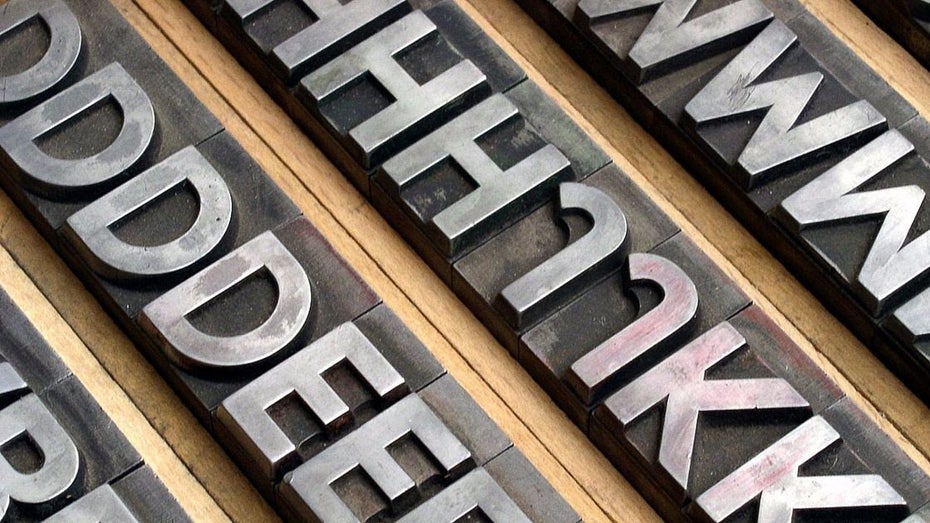
Das Geheimnis guter Typographie: Einfache Tipps für mehr Lesekomfort
Typographie: Schon mit geringstem Aufwand lassen sich Texte deutlich besser lesbar gestalten. (Foto: Pixabay)
Natürlich ist Typographie seit jeher eines der wichtigsten Elemente im klassischen Design. Studierst du Grafikdesign oder verwandte Fächer, so gehört Typographie direkt im ersten Semester zu deinem täglich Brot. Wir wollen hier aber nicht auf akademischen Niveau theoretische Abhandlungen verfassen.
Vielmehr geht es darum, auch dem Nichtdesigner den Wert der Umsetzung typographischer Grundlagen zu vermitteln. Mit den folgenden Tipps gestaltest du deine Texte wesentlich lesbarer und sorgst noch dazu für eine bessere Auffindbarkeit im bereits randvollen Weltennetz.
Beginnen wir mit den Tipps für komfortableres Lesen, die Designer Luke Jones vor wenigen Tagen im InVision-Blog zum Besten gab. Es handelt sich um drei kleine Änderungen, die sich ohne großen Aufwand an jedem Text vollziehen lassen. Nach dem zweiten oder dritten Mal werdet ihr diese Tipps so selbstverständlich anwenden, als hättet ihr es noch nie anders gemacht.
Wenn ihr mehr oder weniger regelmäßig ins Netz schreibt, dann ist euch schon bekannt, dass die Einhaltung der korrekten Hierarchie eines Textes ein wichtiger Faktor für die Auffindbarkeit eurer Inhalte in Suchmaschinen ist. Wahrscheinlich achtet ihr schon aus diesem Grund zumeist auf die richtige Auszeichnung.
Dabei sind es aber nicht nur die Suchmaschinen, die es weitaus leichter haben, sich durch einen sauber strukturierten Text zu arbeiten. Auch eure Leserinnen und Leser profitieren von einer logischen Unterteilung des Inhalts.
Es reicht oft, sich auf die Überschriften der Stufen eins bis drei (h1 – h3), den korrespondierend kleiner gesetzten Fließtext und die noch kleiner gesetzten Fußnoten zu fokussieren. Dafür gibt es ein paar sehr simple Annahmen, anhand derer sich Struktur für jeden Text gut umsetzen lässt.
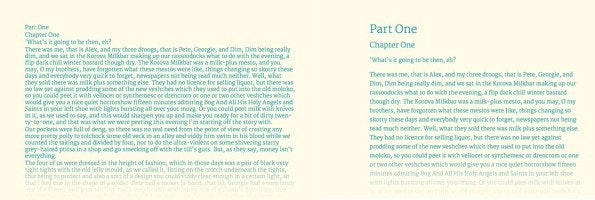
Links seht ihr den Text ohne typographische Grundstrukturen, rechts den gleichen Text mit Struktur. (Screenshot: Luke Jones, InVision Blog)
Ausgangspunkt der Betrachtung ist stets der Fließtext, also das, was wir im Netz in die p-Tags schreiben. Dieser Fließtext ist der Index, hält also die Schriftgröße 100 Prozent. Alle anderen Elemente werden davon abgeleitet.
Zunächst gilt es demnach, den Fließtext auf eine angenehm lesbare Größe zu bringen. Das ist zu einem großen Teil Geschmackssache. Bei mir liegt dieser Wert bei 18 Pixel, kleiner möchte ich es nicht haben. Gängige Publikationen liegen zumeist eher im Bereich um die 14 Pixel. Egal, welche Größe man konkret definiert, stets gilt, dass sie die Grundlage aller weiteren Elemente ist.
Hauptüberschriften (h1) sollten 180 bis 200 Prozent der Ausgangsgröße haben, sekundäre (h2) noch 130 bis 150 Prozent und tertiäre (h3) nurmehr wenig mehr als der Fließtext selbst. Bis 125 Prozent darf man wohl problemlos gehen. Fußnoten und anderer, kleiner gesetzter Text, sollte 75 Prozent der Größe des Fließtext nicht überschreiten.
Auf diese Weise erreichen wir schon durch die Größen unterschiedlicher Textteile eine visuelle Hierarchie, die Orientierung bietet und das Lesen angenehmer gestaltet.
Wir alle sind schon mehr als einmal in Textwüsten verdurstet. Allein der Anblick eines wild dahin gewürfelten Buchstabenhaufens lässt die Kehle spontan trocknen. Dabei ist die Rettung so einfach: Trenne die einzelnen Zeilen sichtbar voneinander und bringe so den Lesefluss zum Strömen. Auch hierfür gibt es einfache Faustformeln.
Der Abstand einer Zeile zur vorhergehenden sollte zwischen 120 und 160 Prozent der Größe des Ausgangstextes entsprechen. Jones gibt als Faustregel den Tipp, dass ein liegendes kleines h in der Ausgangsgröße in den Zwischenraum passen sollte, ohne die oberen und unteren Spitzen der Buchstaben in den beiden Zeilen zu berühren.
Durch klar voneinander getrennte Zeilen lassen sich die Wörter leichter erfassen, was zu einem schnelleren, aber auch angenehmeren Lesen führt. Gleiches gilt für das Setzen des richtigen Abstands zwischen Absätzen. Früher betätigte man einfach die Zeilenschaltung doppelt, was aber in der Regel zu einem zu großen Abstand zwischen den Absätzen führt. Jones empfiehlt daher, für den Abstand die Größe des Ausgangstexte zu verwenden.
Verwender großer Bildschirme kennen sicherlich diese Blogs, deren Betreiber ihre Seite so eingestellt haben, dass sich die Breite des Textes auf die Breite der Anzeige des Besuchers anpasst. Das nennt sich Fluid Design und ist ein valides Gestaltungsmittel, aber nicht in dieser Verwendung.
Als angenehm zu lesen gelten Zeilenlängen von maximal 75 Zeichen, dann sollte ein Umbruch erfolgen. Daraus resultiert der Mehrspaltensatz der altehrwürdigen Holzmedien. Ihr seht, früher war nicht alles schlecht.
Die Einhaltung der genannten Tipps führt unzweifelhaft zu besser lesbaren Texten, die auch gerne konsumiert werden, so denn die Substanz stimmt. Danken wir Luke Jones und schauen noch ein Stück weiter.